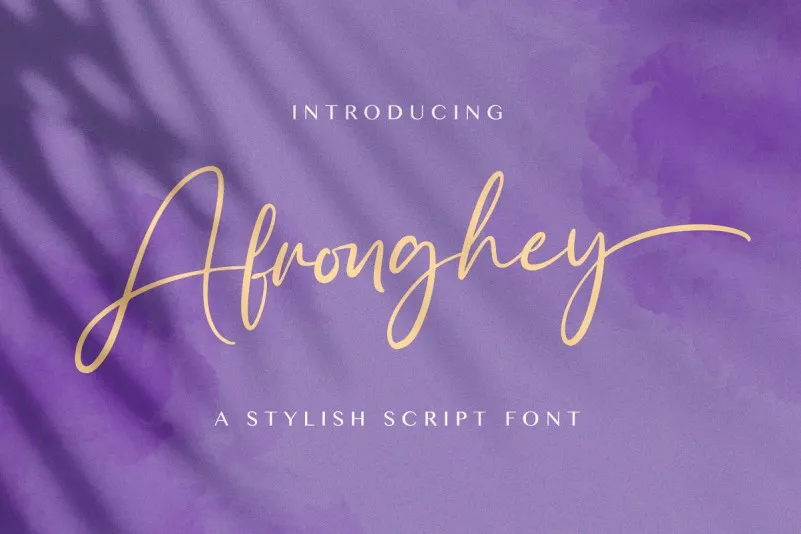
Afronghey Script Font – Fonte Grátis
Afronghey Script Font
Afronghey Script Font é uma tipografia de script que transmite uma sensação autêntica e moderna de escrever com a mão, criada pelo StringLabs. Inspirada na arte do desenho artesanal, esta fonte oferece um formato bem balanceado e elegante dos caracteres, o que a torna perfeita para qualquer projeto de marca ou design digital. Suas formas delicadas e equilibradas permitem que ela se integre em uma ampla variedade de trabalhos criativos. Experimente incorporá-la em seus projetos mais audaciosamente imaginados — notará como ela faz a diferença, transformando suas ideias em algo vivido e real. Com Afronghey Script Font, seu próximo trabalho pode soar e brilhar ainda mais.